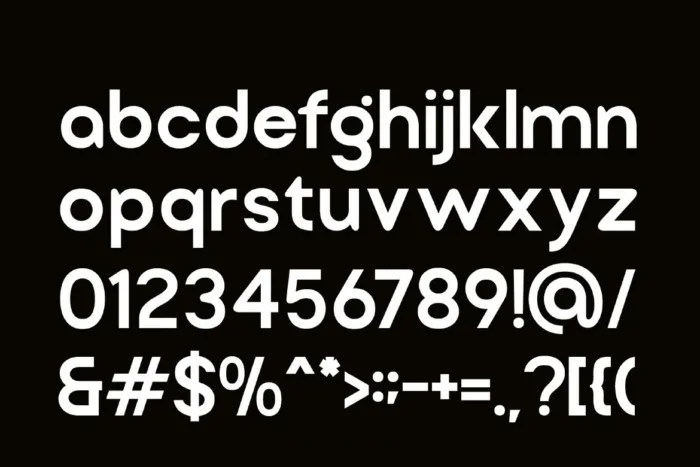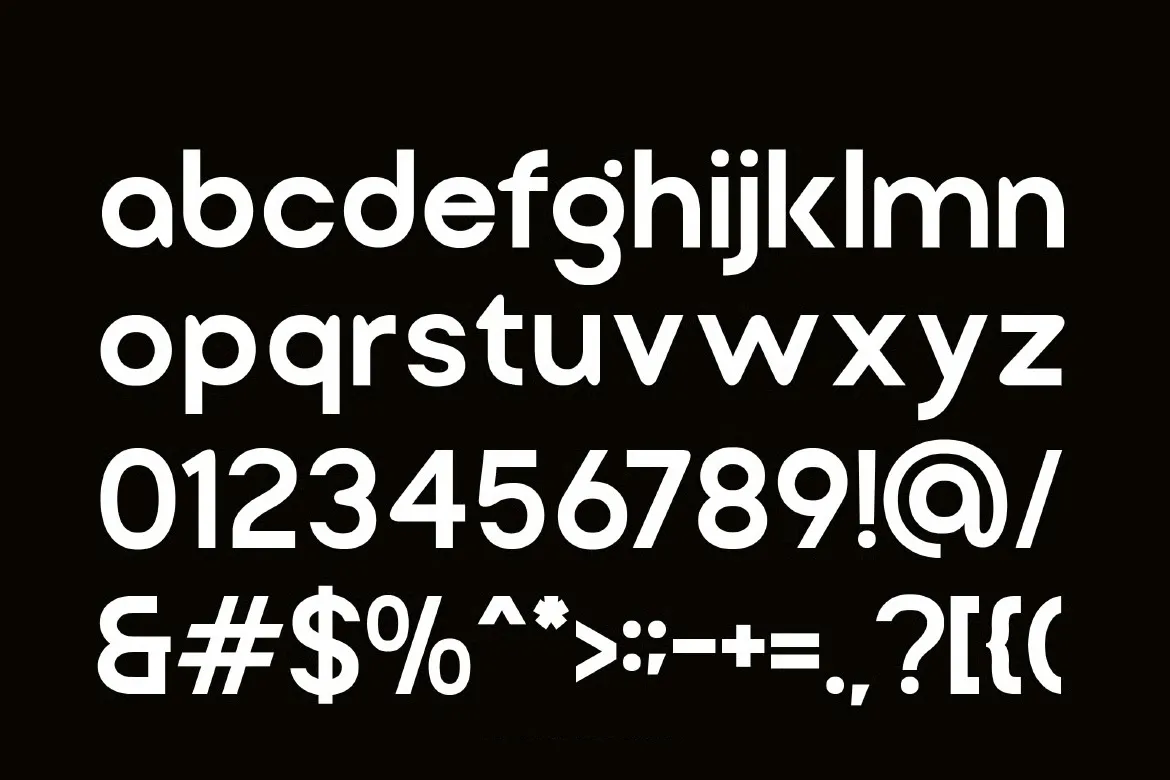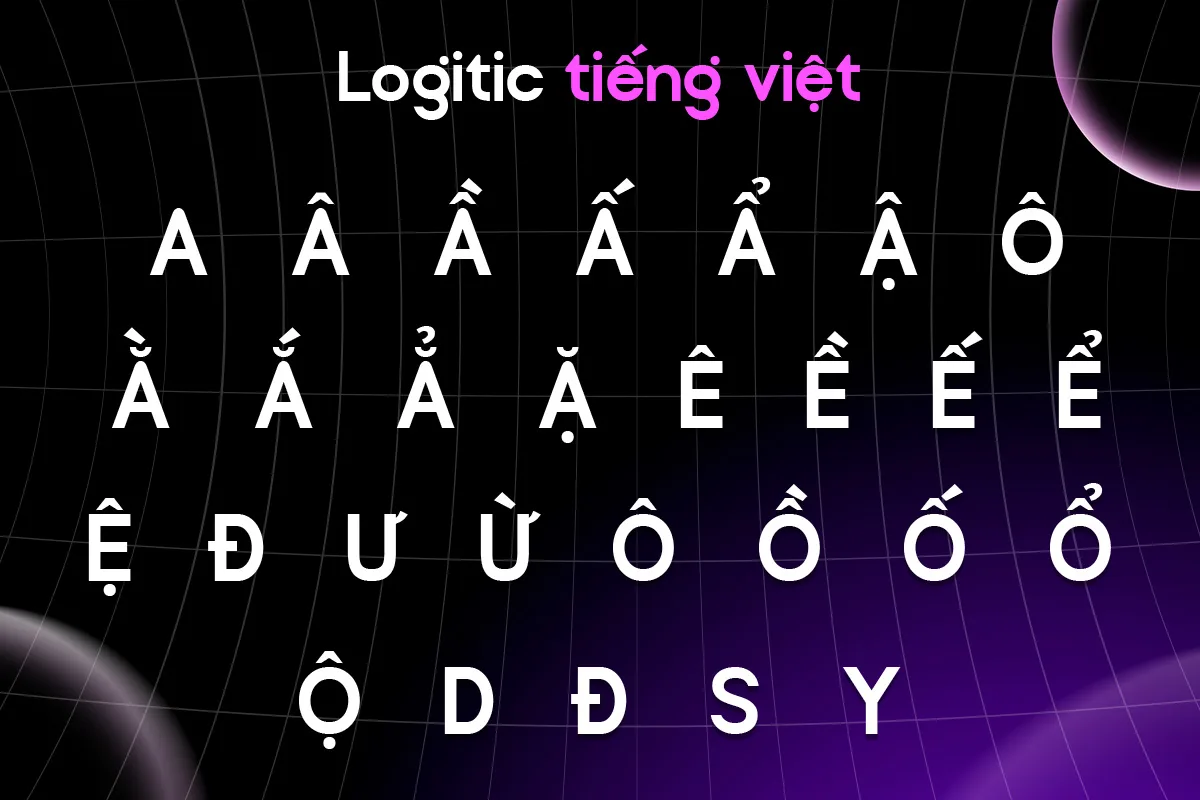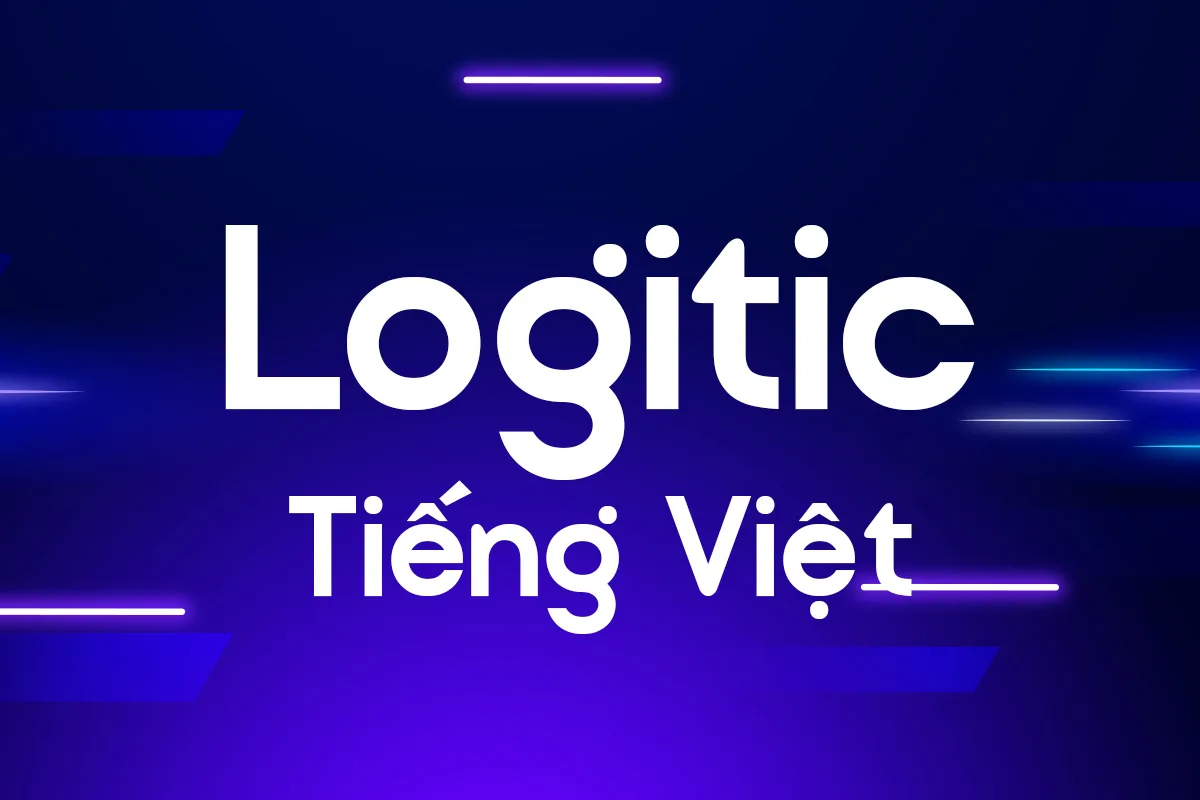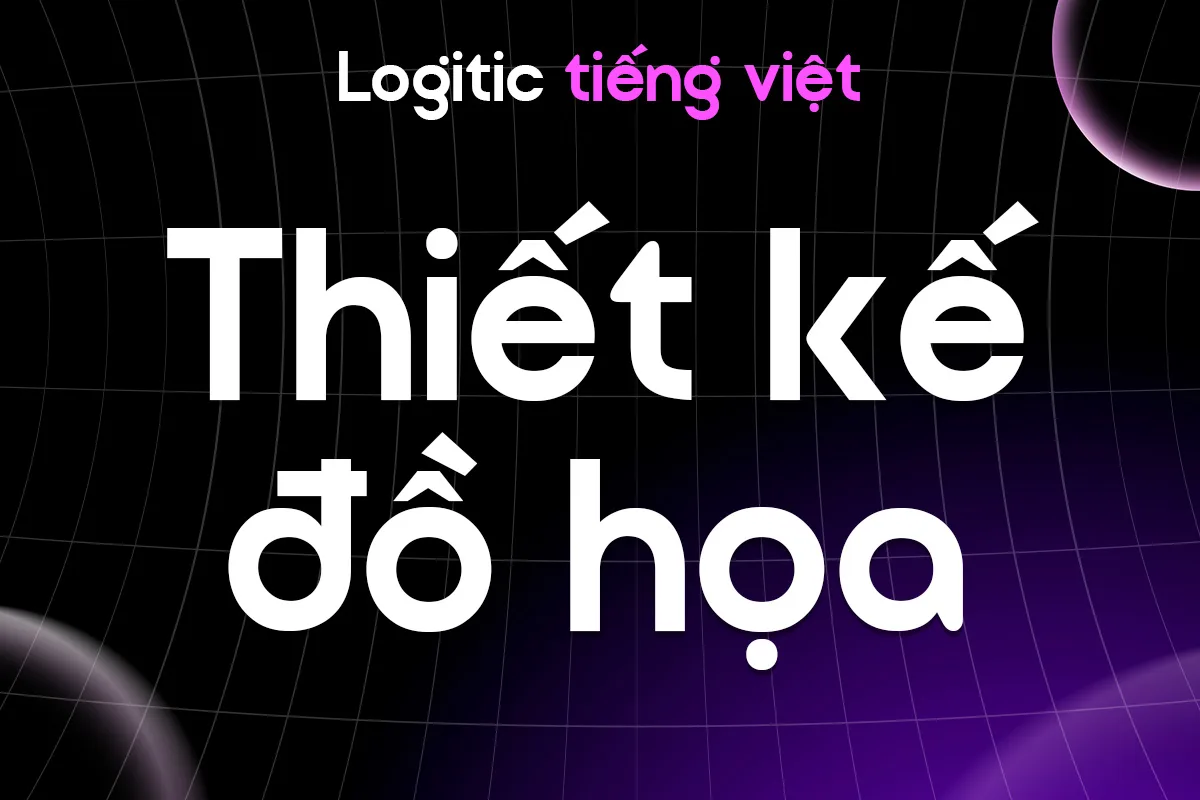
DVN Logitic tiếng Việt – Font chữ đậm chất công nghệ, viễn tưởng thích hợp làm Logo
DVN Logitic là kiểu chữ mang phong cách công nghệ hiện đại và viễn tưởng tương lai, nổi bật với thiết kế hình học mạnh mẽ, tối giản cùng các đường nét bo cong độc đáo. Font mang lại cảm giác digital, AI và cyber-tech cao cấp, phù hợp cho các thiết kế cần sự hiện đại và khác biệt.
Được tối ưu cho logo, gaming, esports, branding công nghệ, UI/UX, poster sci-fi và quảng cáo digital, DVN Logitic giúp tạo điểm nhấn mạnh mẽ với độ nhận diện cao và tinh thần của thế hệ tương lai.